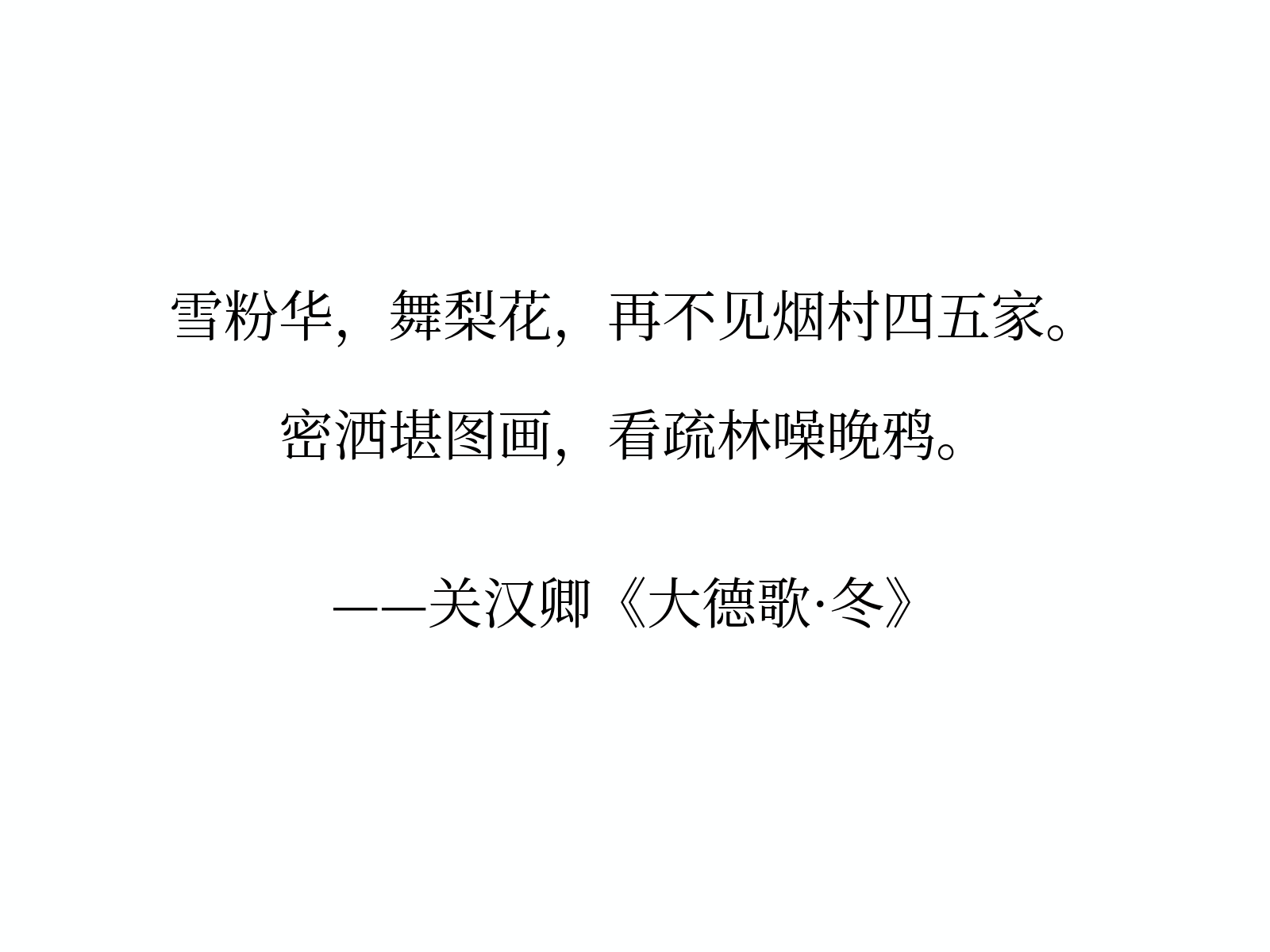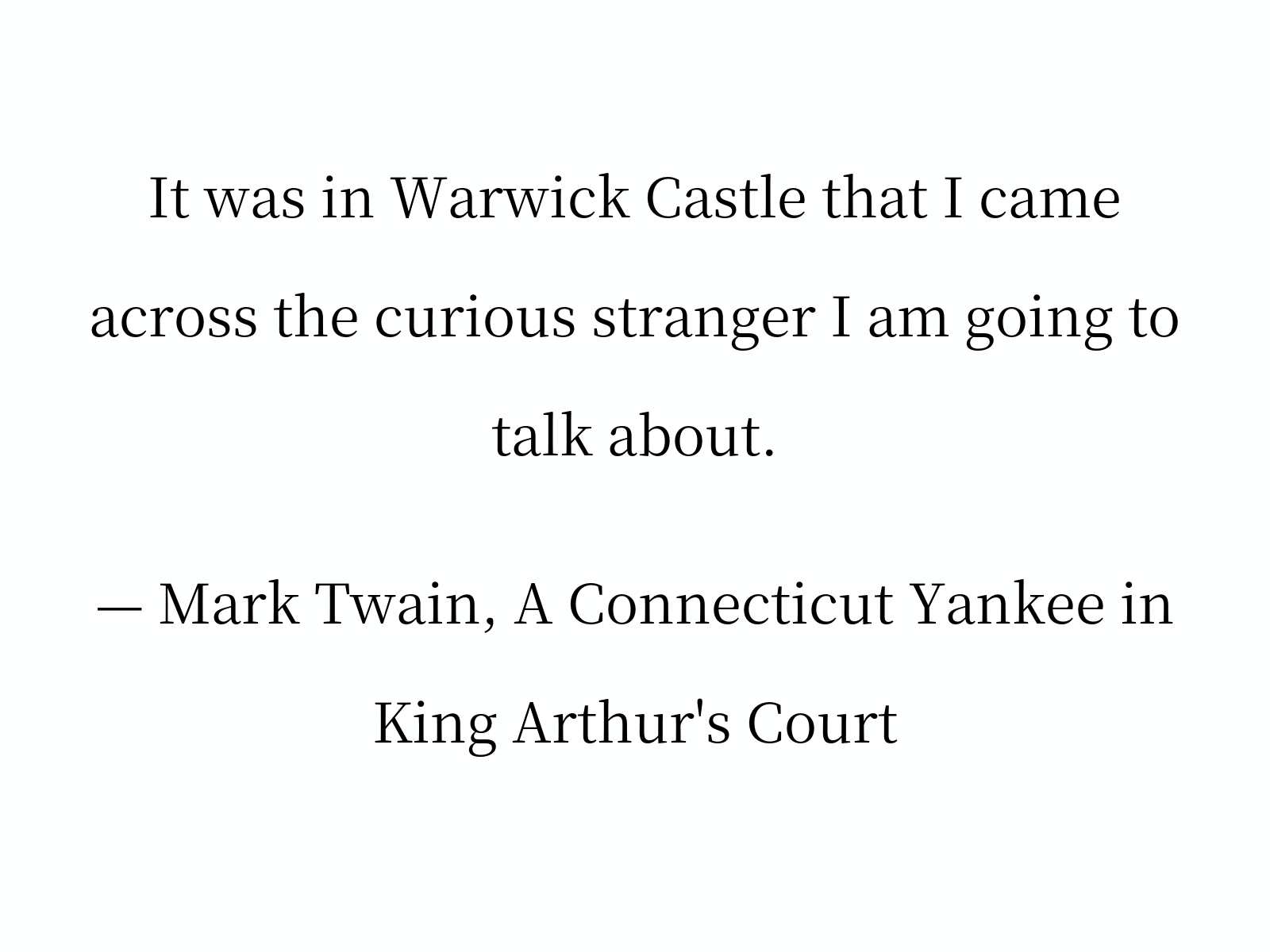
思源宋体是由Adobe与Google联合开发的开源泛CJK字体,旨在为简体中文、繁体中文、日文和韩文提供统一且高质量的排版支持。作为思源黑体的衬线对应版本,它完美融合了传统印刷字体的优雅韵味与现代数字排版的清晰度。该字体家族共包含7种字重(从ExtraLight到Heavy),每种字重均收录了65,535个字形,总计近46万个字符,全面覆盖了GB 18030、《通用规范汉字表》以及日韩常用字符集,并针对不同语言的字形差异进行了精心优化。思源宋体采用OpenType格式,不仅适用于书籍报刊等长文阅读,也胜任品牌设计与屏幕显示。其西文部分基于Source Serif设计,确保了多语言混排时的和谐统一。最重要的是,它以SIL Open Font License 1.1协议开源,允许免费用于任何个人及商业项目。